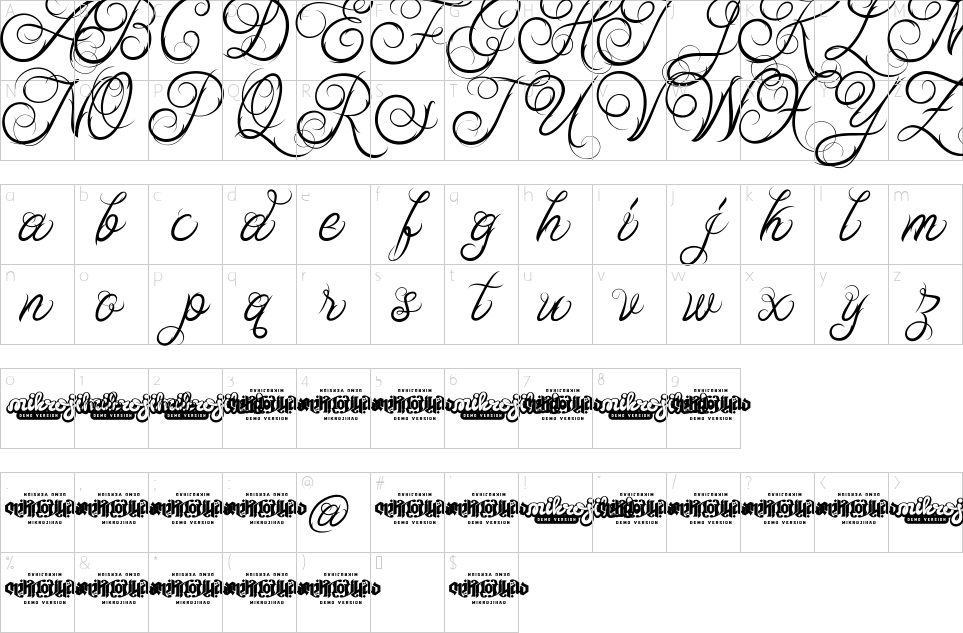
A Ababil Script é uma fonte elegante e sofisticada ideal para gráficos e desenhos em grande estilo. Inspirada na cultura árabe, essa fonte oferece uma escrita fluida e curvilínea que se destaca em qualquer projeto. Com a Ababil Script, você pode adicionar um toque de originalidade a qualquer design de logotipo, banner ou design gráfico. A fonte foi desenvolvida pela empresa Mikrojihad Inc e já foi baixada mais de 25,000 vezes. Se você está buscando uma fonte única e versátil, a Ababil Script é uma ótima escolha. Descubra por si mesmo qual impacto essa fonte pode criar para seu trabalho.